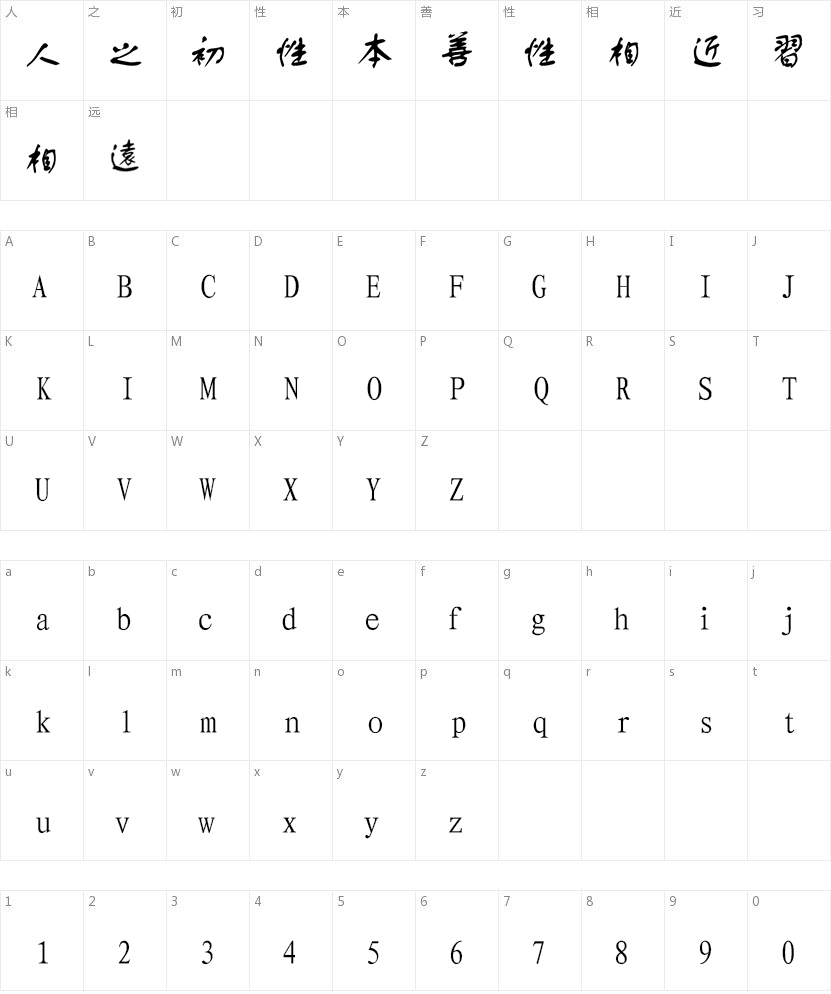
长城行书体繁字体是一种中国传统的行书体字体,它的特点是字形细腻,笔画流畅,笔划细致,结构严谨,行书的结构清晰,笔画均匀,曲折有序,构成字体的组成部分紧凑,字形结构完整,行书的节奏自然,每个字的笔画都有节奏感,字体形态自然,行书的结构完整,字形比例较为合理,笔画与笔画之间的联系清晰,行书的结构紧凑,字体看起来自然,稳重大气,具有浓郁的中国传统文化气息。文件名:ChangChengXingShuTiFan-1.ttf
长城行书体繁是一款非常不错的手写艺术字体,具有很好的视觉感,适合于文化类的宣传设计、商业类品牌的广告和产品包装设计以及个性化文字排版等较多场景。